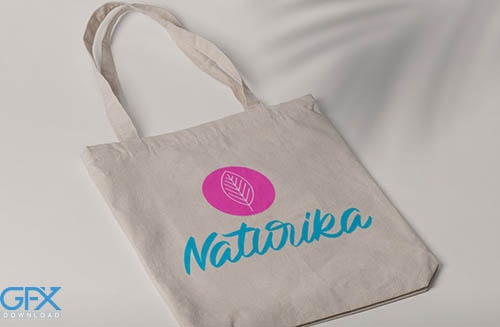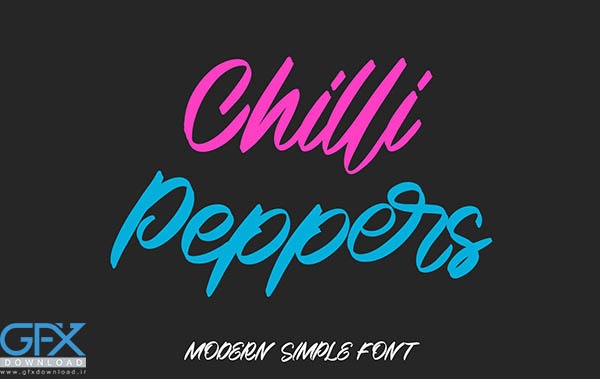
فونت انگلیسی Chilli Peppers
دانلود فونت Chilli Peppers یک فونت اسکریپت شیک، عجیب و غریب و فوق العاده متمایز است. احساس برجسته آن باعث می شود که این فونت به طرز باورنکردنی همه کاره باشد و با طیف وسیعی از زمینه ها مطابقت داشته باشد. چه از آن برای برندسازی، طراحی دیجیتال، ارائه، پوستر، لوگو، رویداد یا ساخت کارت تبریک استفاده کنید، عالی است! این فونت دارای کد PUA است که به این معنی است که می توانید به راحتی به همه حروف های عالی دسترسی داشته باشید! همچنین دارای تعداد زیادی از ویژگی های خاص از جمله لیگاتور است.
• پشتیبانی از چند زبانه
• اعداد و علائم نگارشی
• حروف کوچک و بزرگ
• لیگاتور